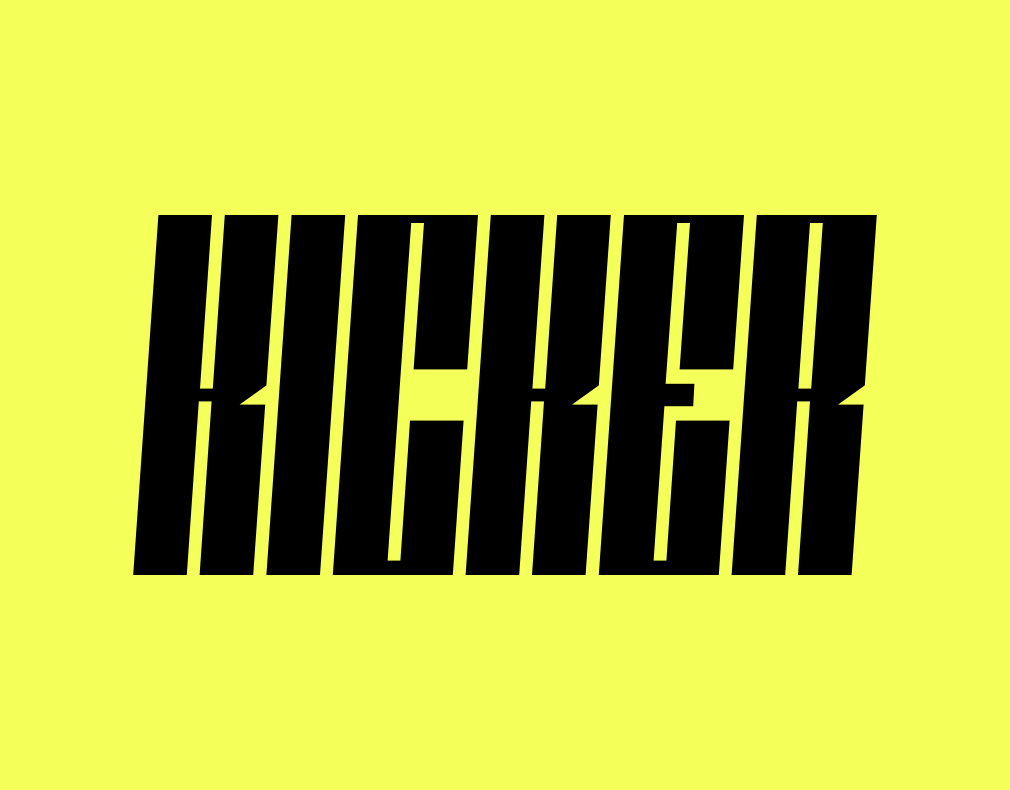
Kicker é uma fonte em letras maiúsculas para uso expositivo que se destaca por sua aparência bruta e agressiva. Ideal para headlines, esta fonte foi criada com um objetivo claro: chamar a atenção do leitor. Composta de blocos retangulares e linhas finas, Kicker apresenta uma versão regular e outra em obliqüidade. Esta elegante fonte está disponível gratuitamente tanto para uso pessoal quanto comercial. Quer destacar seus projetos com um visual forte? Descubra por si mesmo a diferença que Kicker pode fazer!